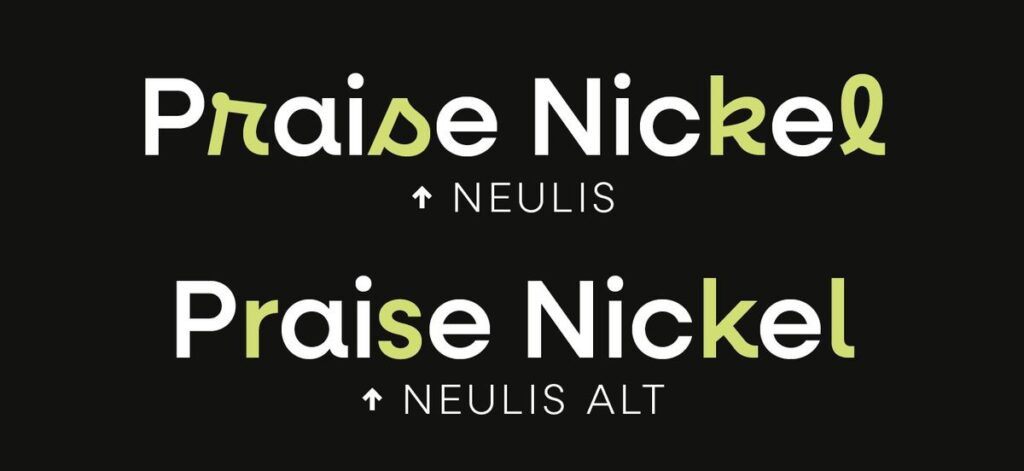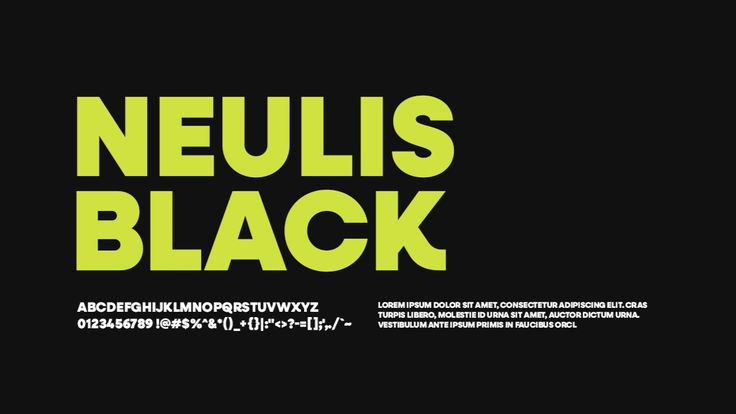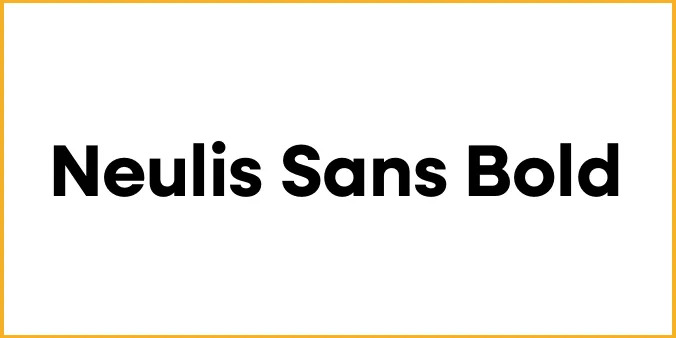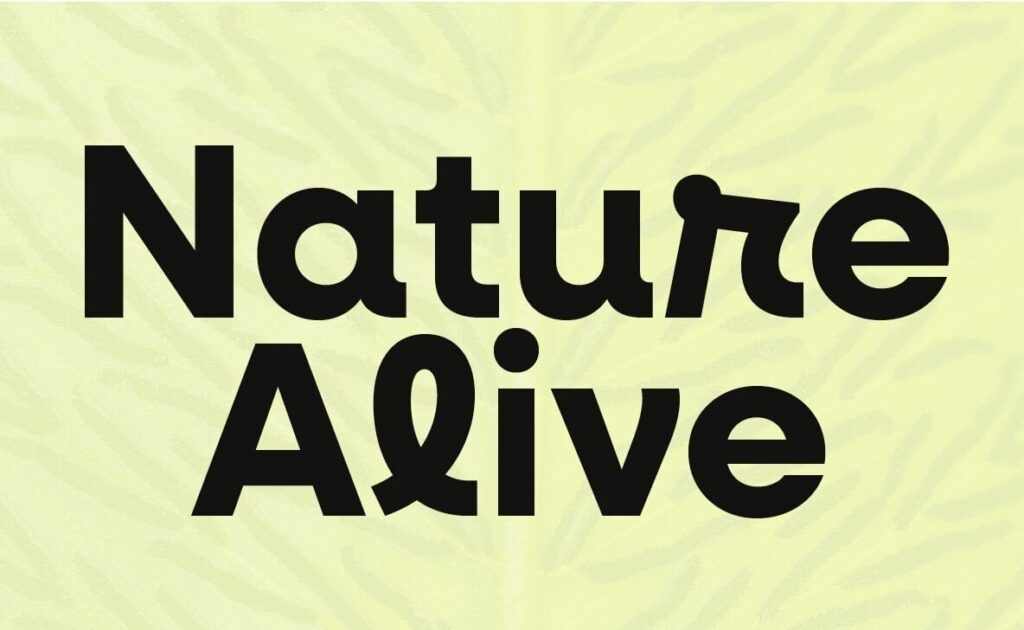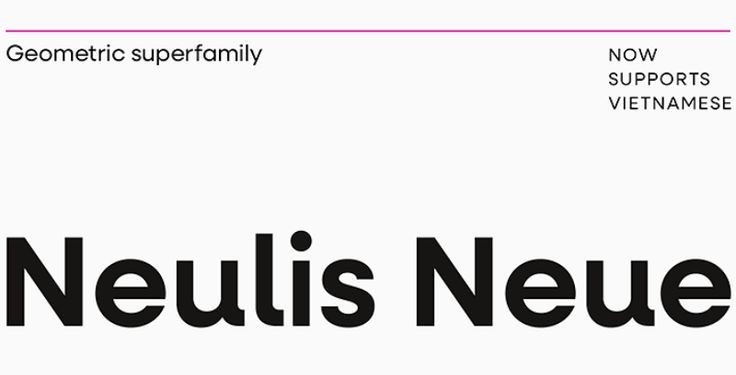
Font Neulis là bộ phông chữ thuộc dòng Sans-serif gây ấn tượng bởi sự giao thoa giữa cấu trúc hình học chuẩn xác và những đường nét nhân bản mềm mại. Đây là lựa chọn lý tưởng cho các nhà thiết kế muốn thể hiện phong cách hiện đại, tinh gọn nhưng vẫn giữ được sự gần gũi.
Đặc điểm thẩm mỹ nổi bật của dòng font Neulis Việt hóa
Nét lôi cuốn đặc trưng của Neulis nằm ở độ mở ký tự rộng và các nét chữ được tính toán kỹ lưỡng để duy trì sự thông thoáng. Khác với các dòng phông chữ không chân truyền thống, font neulis-neue sở hữu các đường bo góc tinh tế, tạo nên một dòng chảy văn bản tự nhiên và dễ tiếp nhận. Phiên bản font Neulis Việt hóa free đã được xử lý bảng mã Unicode một cách tỉ mỉ, giúp các dấu thanh không bị chồng chéo hay lệch tông, đảm bảo tính thẩm mỹ ổn định cho các văn bản tiếng Việt.
| Phân loại phong cách | Humanist Sans-serif / Geometric / Modern |
| Các biến thể tiêu biểu | Light, Regular, Medium, Bold, ExtraBold |
| Mục đích phù hợp | Hồ sơ dự án, Website, Bảng hiệu, Poster |
Gợi ý lựa chọn: Để bản thiết kế đạt được hiệu quả thị giác hài hòa, bạn nên sử dụng các biến thể Bold cho đề mục chính và dùng kiểu Regular cho phần thuyết minh chi tiết. Việc sử dụng đồng bộ gia đình font Neulis sẽ giúp hồ sơ năng lực của đơn vị thi công trông chuyên nghiệp và có chiều sâu hơn.
03 Lưu ý kỹ thuật để bố cục font Neulis đạt độ rõ nét cao
Để khai thác hiệu quả vẻ đẹp của dòng font Sans-serif đa năng này mà không làm rối mắt người xem, người thiết kế nên lưu tâm một số kinh nghiệm sau:
- Kiểm soát khoảng cách dòng: Với cấu trúc chữ có độ mở lớn, bạn nên thiết lập khoảng cách dòng thoáng một chút (khoảng 1.4 – 1.5 lần cỡ chữ) để văn bản không bị bết dính, giúp người đọc cảm thấy thoải mái hơn khi tiếp nhận nội dung.
- Lựa chọn trọng lượng nét phù hợp: Hãy tận dụng biến thể Bold của font Neulis việt hóa cho các tiêu đề quan trọng. Tránh sử dụng quá nhiều kiểu đậm trong cùng một đoạn văn để duy trì sự thanh thoát cho trang giấy.